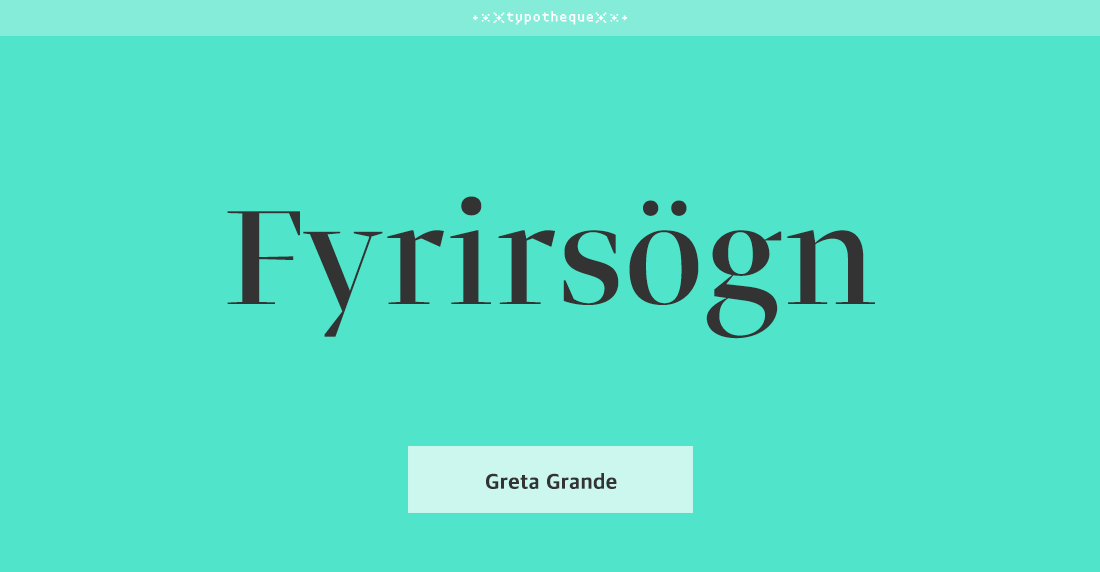
Greta Grande Std
Greta Grande Narrow Std는 큰 헤드 라인을 대상으로 하며 두껍고 좁은 간격 및 속공간 사이의 대비를 고려하여 설계되었다.
헤드라인에 가장 적합하고 다른 Greta 폰트와 함께 쓴다면 더할 나위 없이 완벽한 디자인을 완성할 수 있을 것이다.
- 2008
- Nikola Djurek PeterBiľak
- Serif